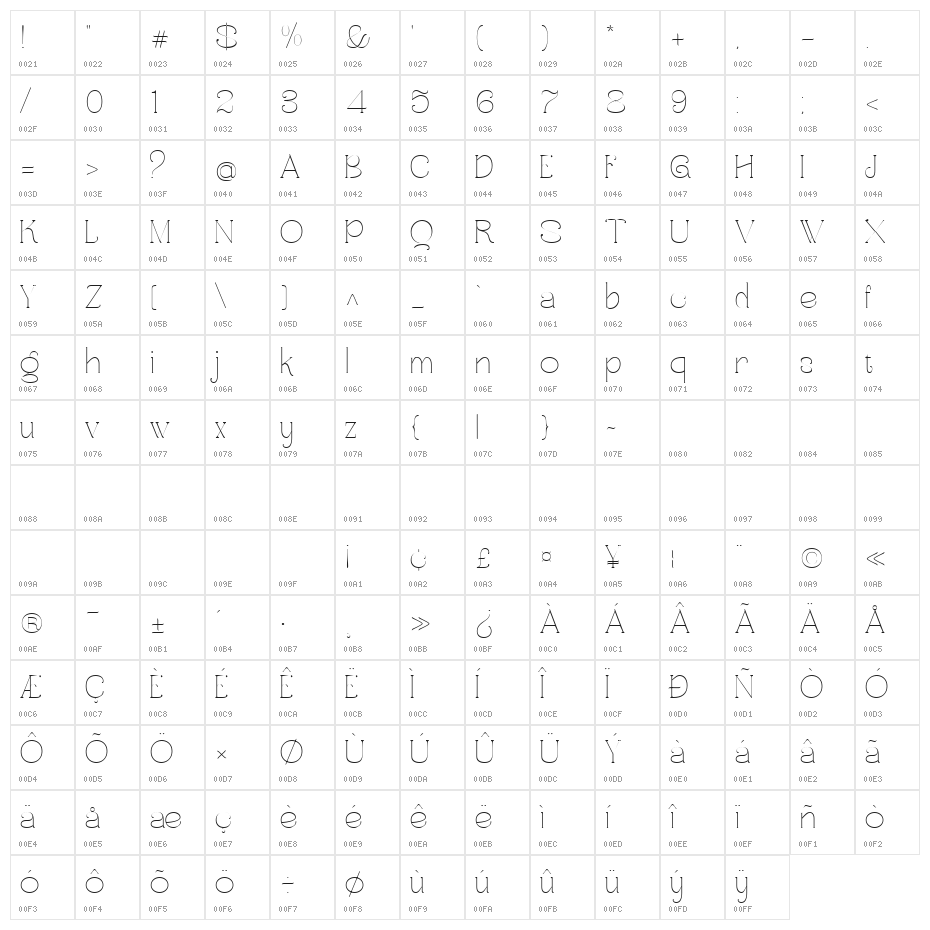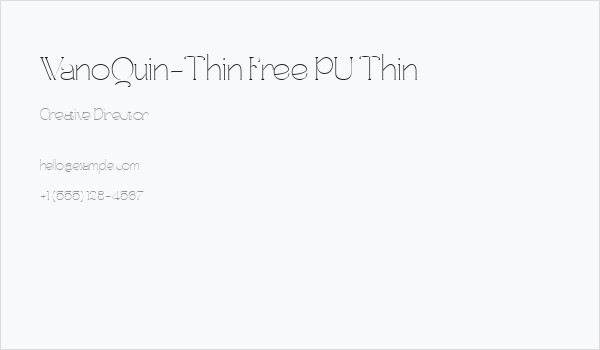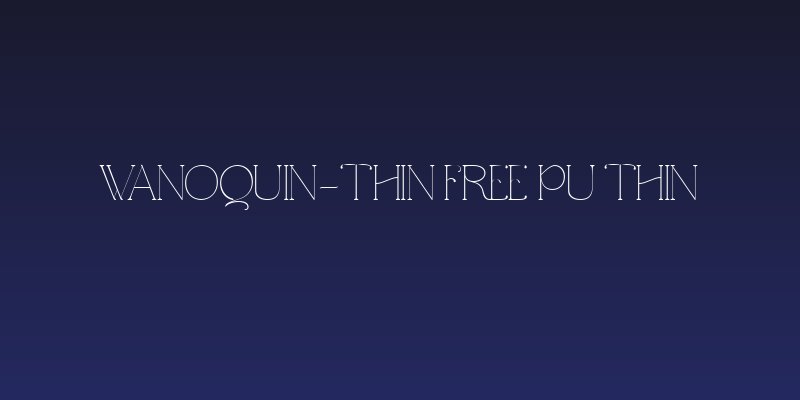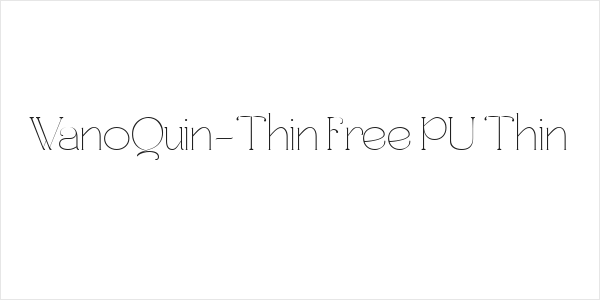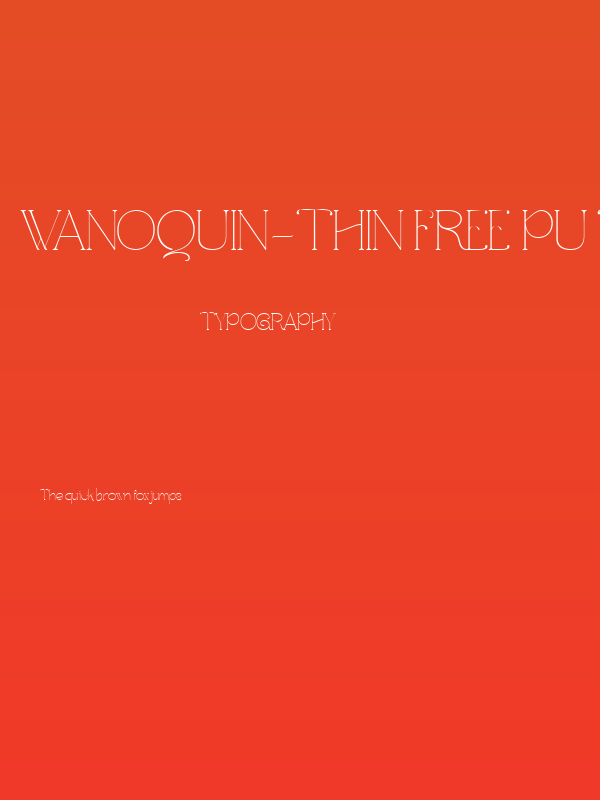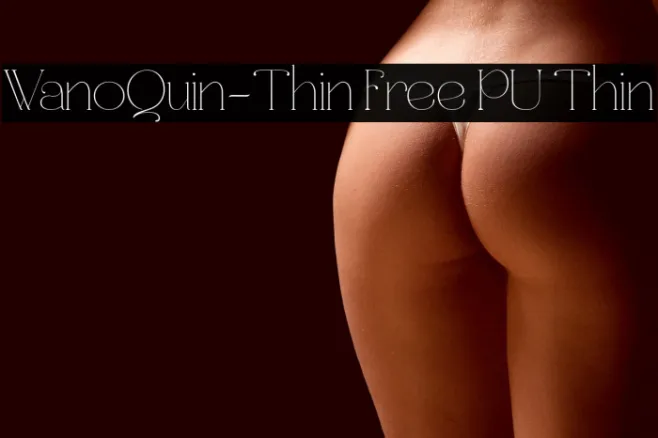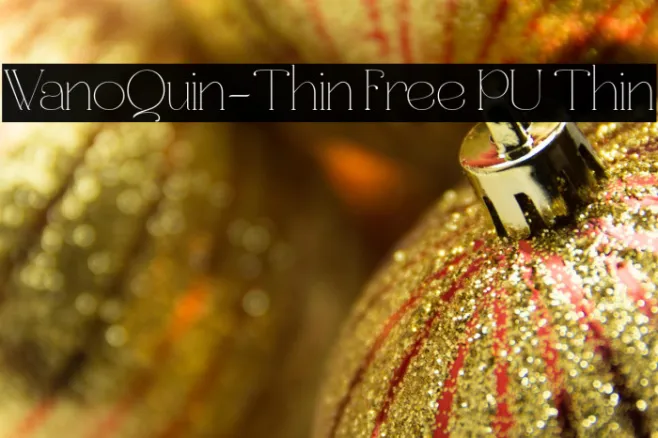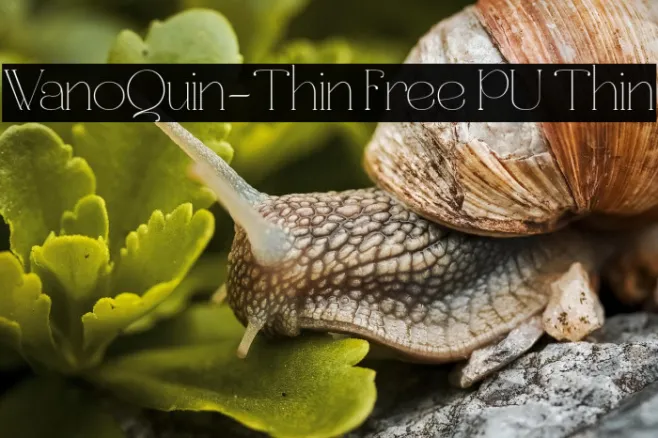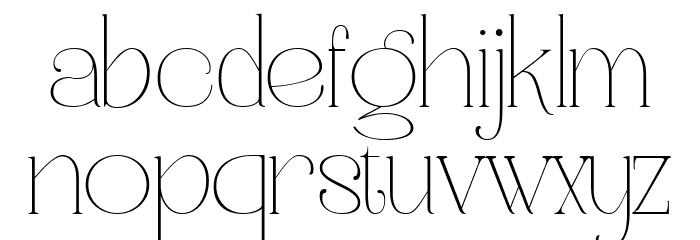
WanoQuin-Thin Free PU Thin Font
| Estilo general | Elegant and sophisticated |
| Caso de uso | Logos, Invitations, Headlines |
| Proyectos propuestos | Ideal for luxury branding, wedding invitations, fashion magazines, and high-end product packaging. |